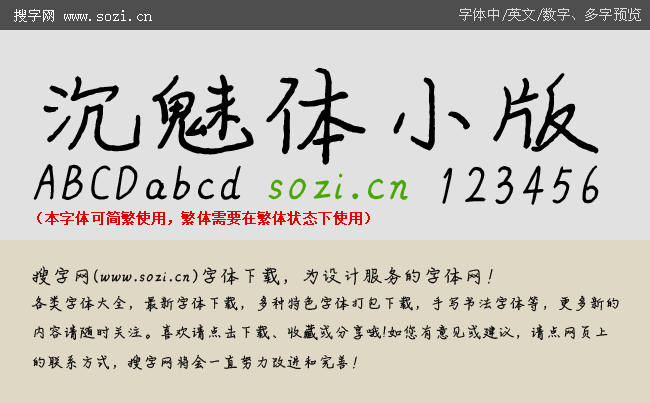
沉魅體小版
搜字網(wǎng)給大家提供一款手寫(xiě)風(fēng)格的沉沉魅體小版手機(jī)中文字體下載。這款手機(jī)字體是一款手寫(xiě)風(fēng)格硬筆行書(shū)書(shū)法字體,字體書(shū)寫(xiě)流暢,瀟灑大方,特別適合喜歡書(shū)法的朋友在手機(jī)上安裝使用。